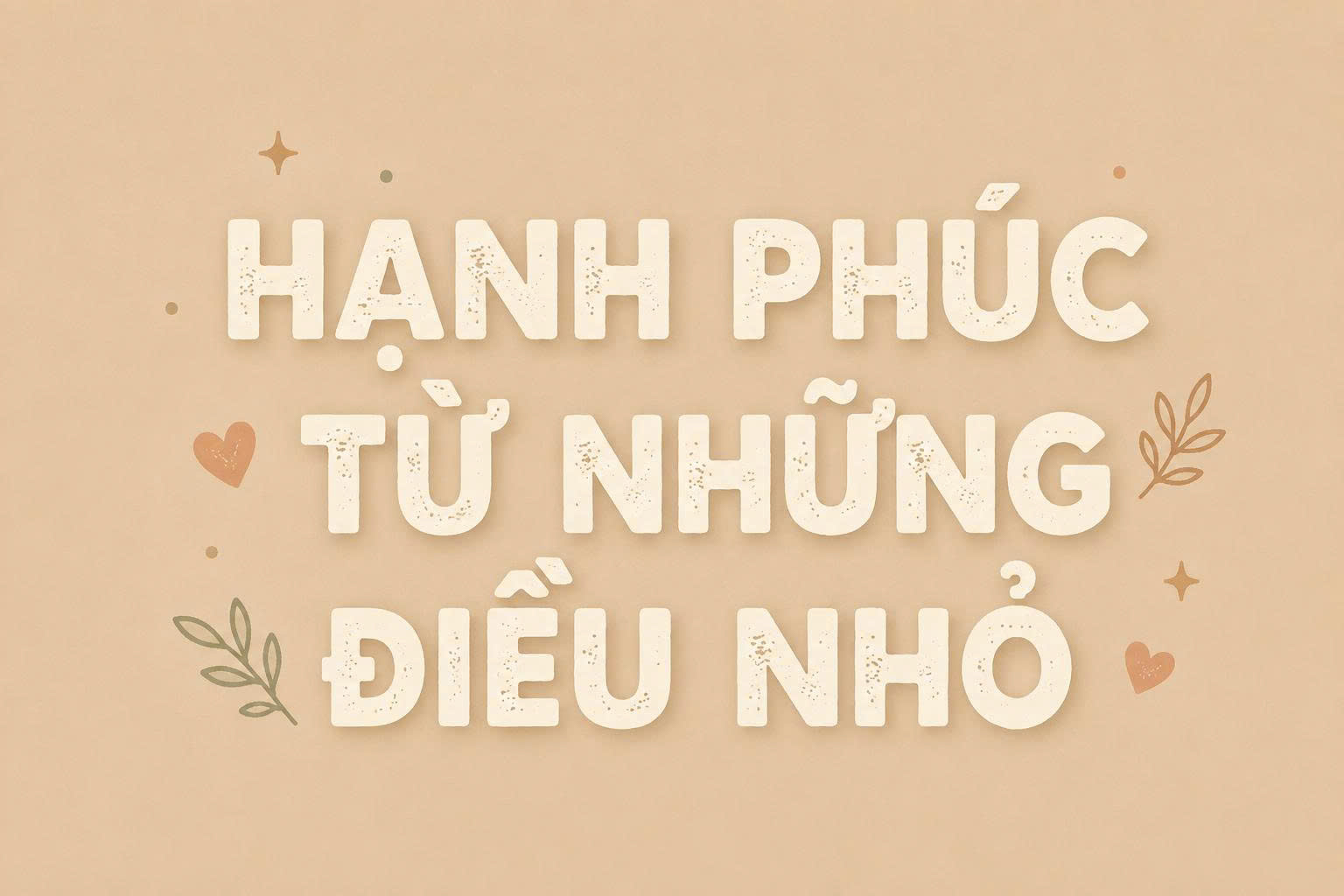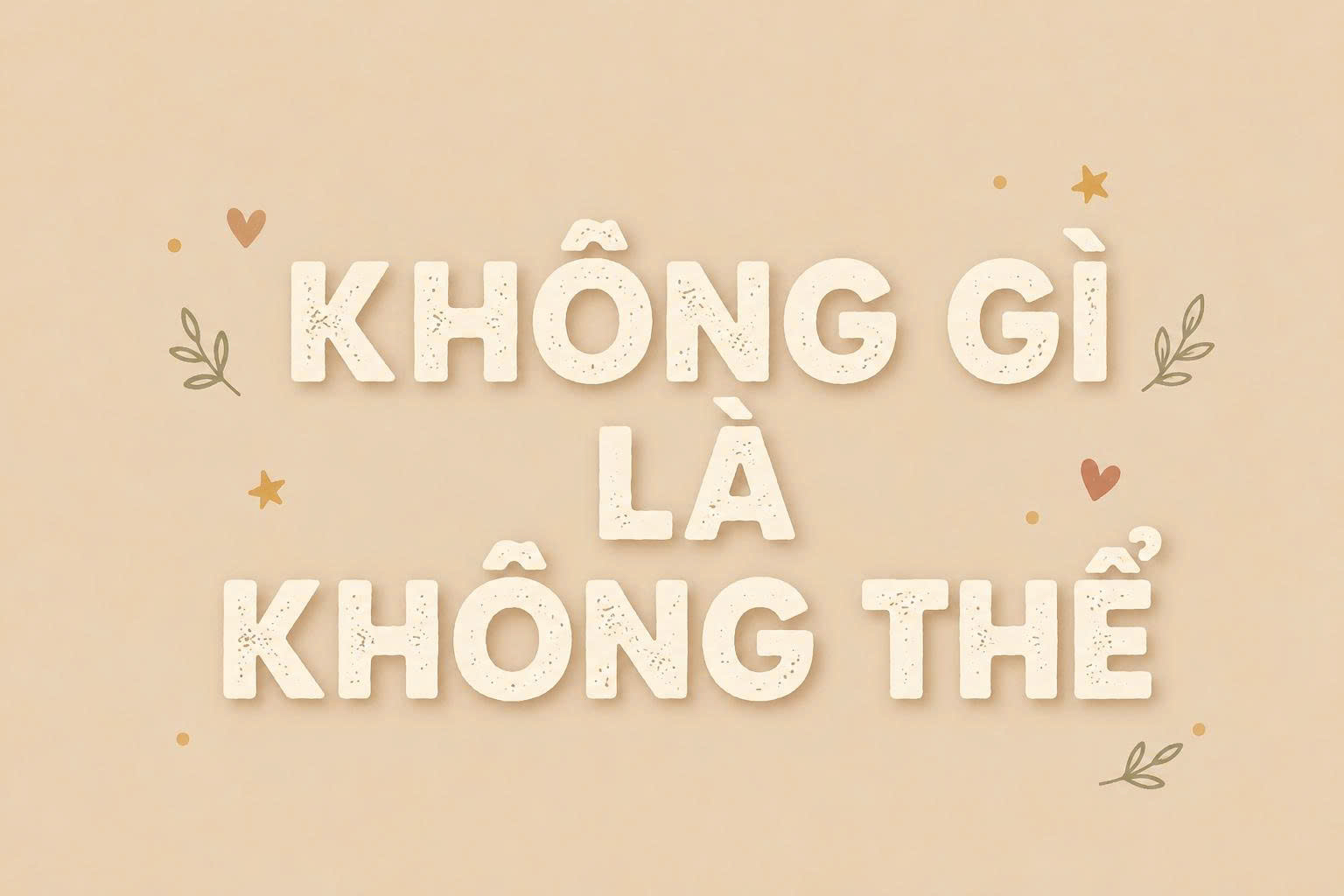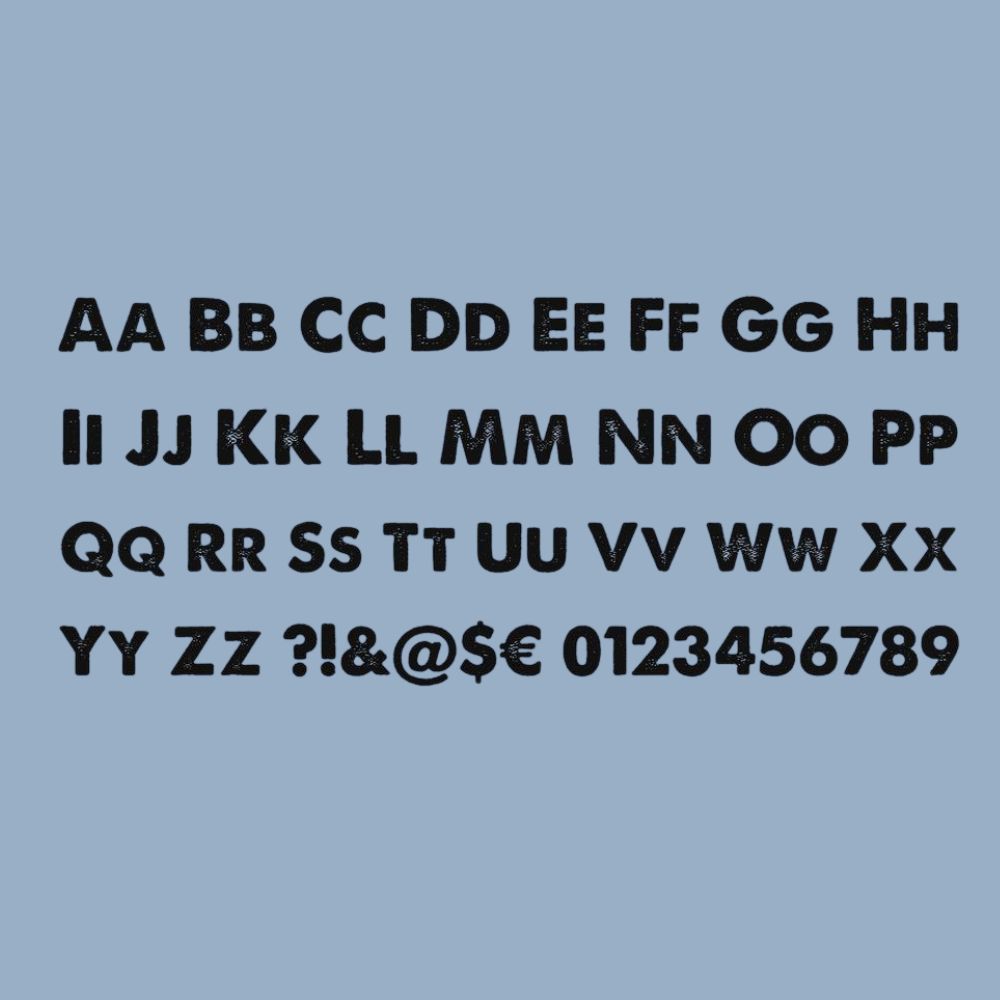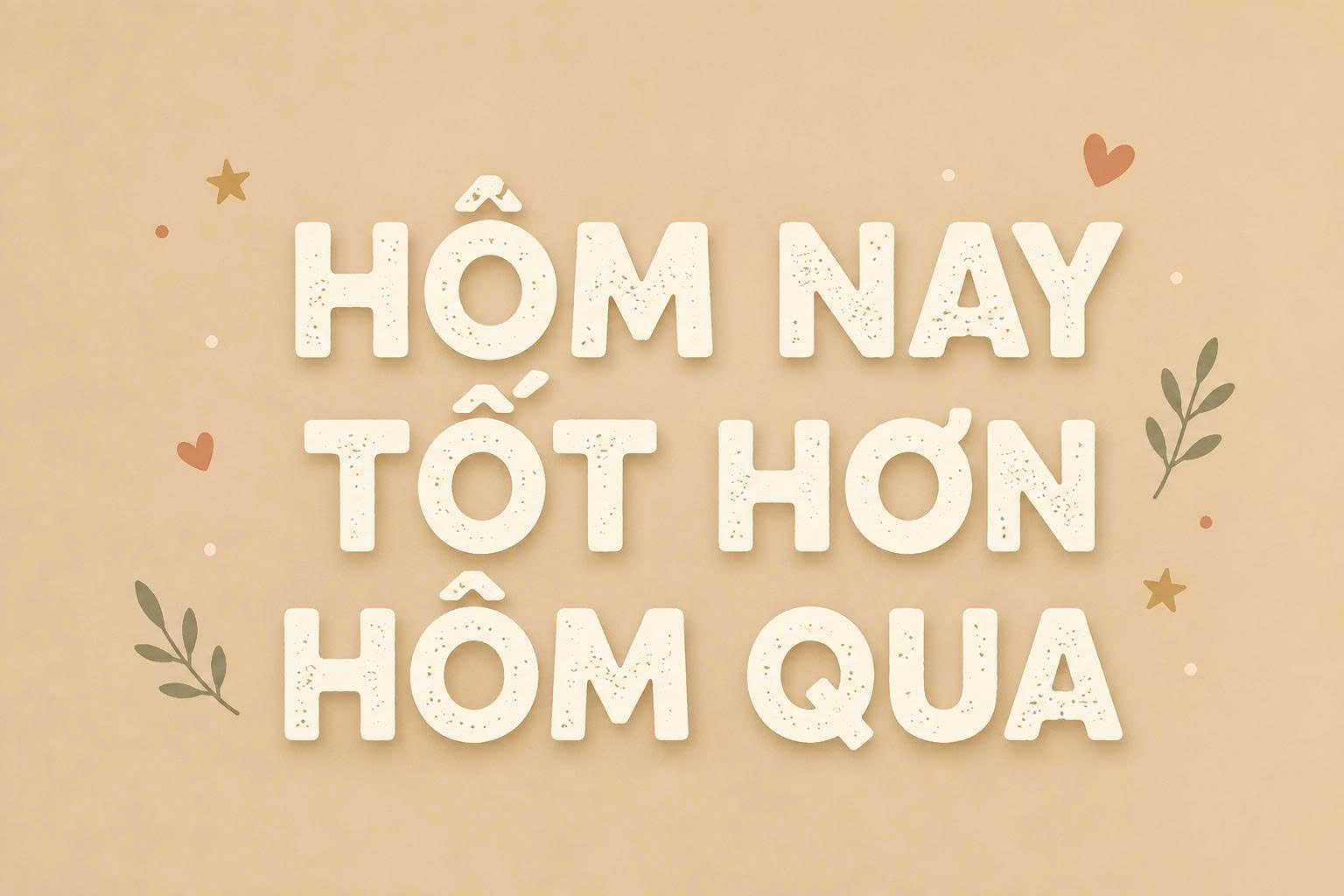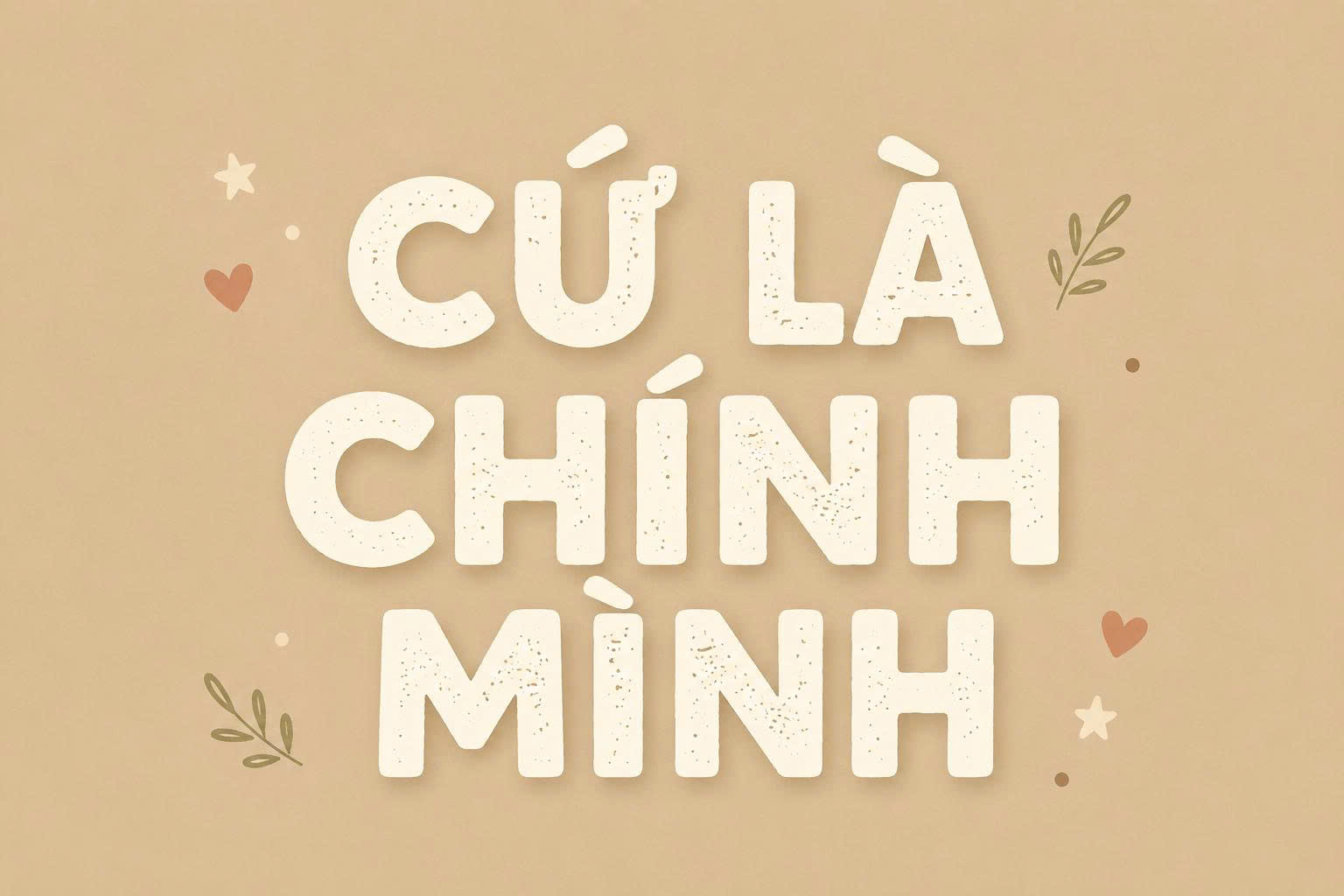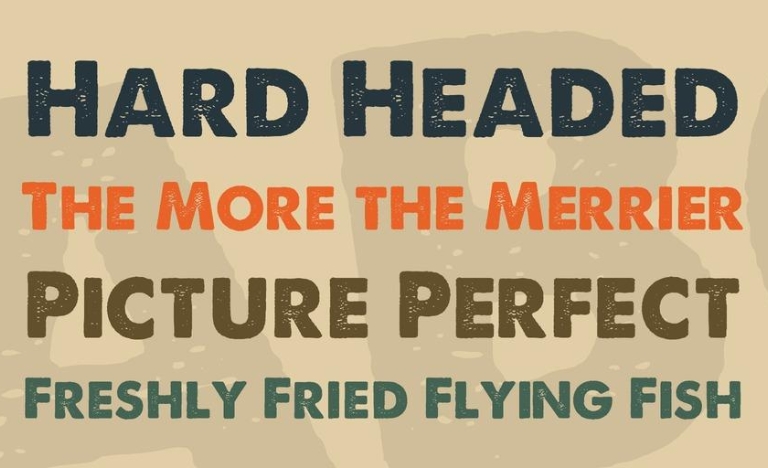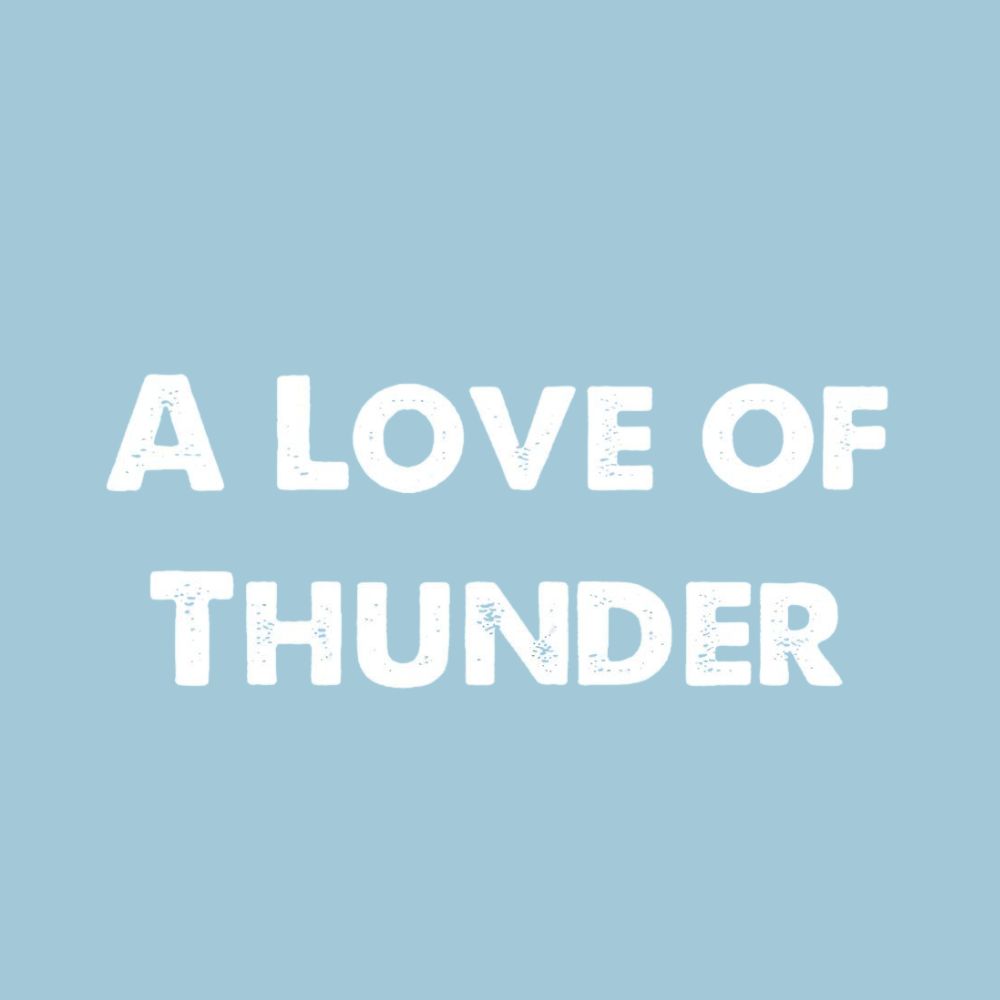
Font Việt hóa SVN A Love of Thunder là một bộ font chữ mang phong cách viết tay đầy ngẫu hứng và phóng khoáng, gợi lên cảm hứng về sự tự do và sáng tạo không giới hạn. Với những đường nét bay bổng nhưng vẫn giữ được sự chắc chắn trong cấu trúc, bộ font này thường được ưu tiên cho các dự án thiết kế cần tạo ấn tượng mạnh về mặt cảm xúc.
Đặc điểm nổi bật của font Việt hóa SVN A Love of Thunder
Điểm khác biệt của SVN A Love of Thunder nằm ở sự kết hợp giữa nét chữ script hiện đại và phong cách grunge bụi bặm. Các ký tự được thiết kế với độ cao không đồng nhất một cách có ý đồ, tạo nên nhịp điệu tự nhiên như chữ viết tay thực thụ. Phiên bản font svn a love of thunder việt hóa đã được xử lý kỹ lưỡng các dấu thanh tiếng Việt, giúp tổng thể văn bản trông cân đối và chuyên nghiệp, tránh được các lỗi hiển thị phổ biến trên những bộ font ngoại lai.
Bên cạnh đó, bộ font này sở hữu khả năng truyền tải thông điệp rất tốt thông qua vẻ ngoài cá tính. Dù được sử dụng cho các tiêu đề lớn hay các đoạn trích dẫn ngắn, SVN A Love of Thunder vẫn duy trì được độ rõ nét và sức hút riêng biệt. Đây là lựa chọn phù hợp cho những ai muốn tìm kiếm sự phá cách, thoát khỏi những khuôn mẫu font chữ truyền thống cứng nhắc.
| Tên đầy đủ | SVN-A Love of Thunder |
| Phong cách thiết kế | Handwritten, Script, Artistic |
| Lĩnh vực ứng dụng | Branding, Poster, Decor, Bao bì |
Lời khuyên từ chuyên viên: Font chữ này mang sắc thái mạnh mẽ và có phần nổi loạn. Bạn nên kết hợp nó với những hình ảnh có chiều sâu hoặc các tông màu trầm, tối để làm nổi bật vẻ đẹp hoang dại và tinh tế của từng nét chữ.
03 Ứng dụng font SVN A Love of Thunder vào thực tế thiết kế
Nhờ vẻ ngoài giàu tính nghệ thuật, bộ font này mang lại giá trị thẩm mỹ cao khi được đưa vào các hạng mục quảng bá và trang trí không gian:
- Nhận diện thương hiệu cho khu nghỉ dưỡng: Những nét chữ phóng khoáng của font chữ này rất ăn ý khi xuất hiện trên logo hoặc bảng hiệu của các khu homestay container, nhà lắp ghép mang phong cách tự do, gần gũi với thiên nhiên.
- Thiết kế Poster và bìa sách: Với cá tính mạnh, SVN A Love of Thunder giúp các ấn phẩm truyền thông trở nên lôi cuốn hơn, dễ dàng tạo ra sự kết nối về mặt cảm xúc với người xem ngay từ cái nhìn đầu tiên.
- Trang trí nội thất hiện đại: Bạn có thể dùng font chữ này để cắt chữ nổi hoặc in decal trang trí tại các văn phòng sáng tạo, quán cafe hoặc không gian sống cá nhân nhằm tạo điểm nhấn đầy nghệ thuật.
03 Lưu ý khi sử dụng font SVN A Love of Thunder trong bố cục
Để bộ font này phát huy tối đa hiệu quả mà không gây rối mắt cho người xem, bạn nên lưu tâm một số kinh nghiệm sau:
- Điều chỉnh khoảng cách dòng (Leading): Do một số nét chữ có xu hướng vươn cao hoặc hạ thấp, bạn nên nới rộng khoảng cách giữa các dòng để tránh tình trạng các nét ký tự bị chồng lấn lên nhau.
- Ưu tiên dùng làm điểm nhấn: Tránh sử dụng font chữ này cho các đoạn văn bản dài hoặc các hồ sơ thông số kỹ thuật. Hãy để SVN A Love of Thunder tỏa sáng ở vị trí tiêu đề hoặc các câu slogan quan trọng.
- Phối hợp font chữ thông minh: Để tạo ra sự cân bằng cho bản thiết kế, bạn hãy phối hợp font script này với một font chữ không chân (Sans Serif) đơn giản và gọn gàng cho phần nội dung phụ.